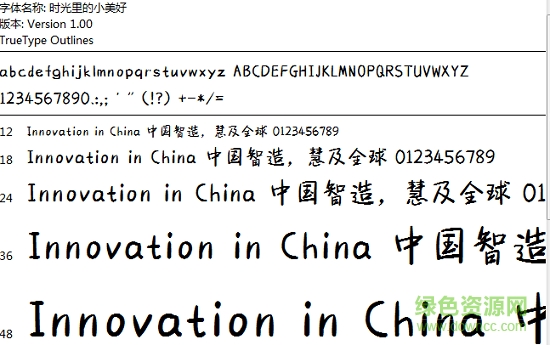
qq時(shí)光里的小美好字體是一款非常好看的中文手寫字體,這款字在有些地方的連筆處理顯得非常的生動(dòng),將一款比較正式的字體瞬間變得活潑、靈動(dòng),感興趣歡迎下載!
qq時(shí)光里的小美好字體是qq中一款非常好看的字體,這款字體是方正專為手機(jī)用戶打造的,采用手寫風(fēng)格,并且融入黑體字體的特色,使得效果變得明顯!